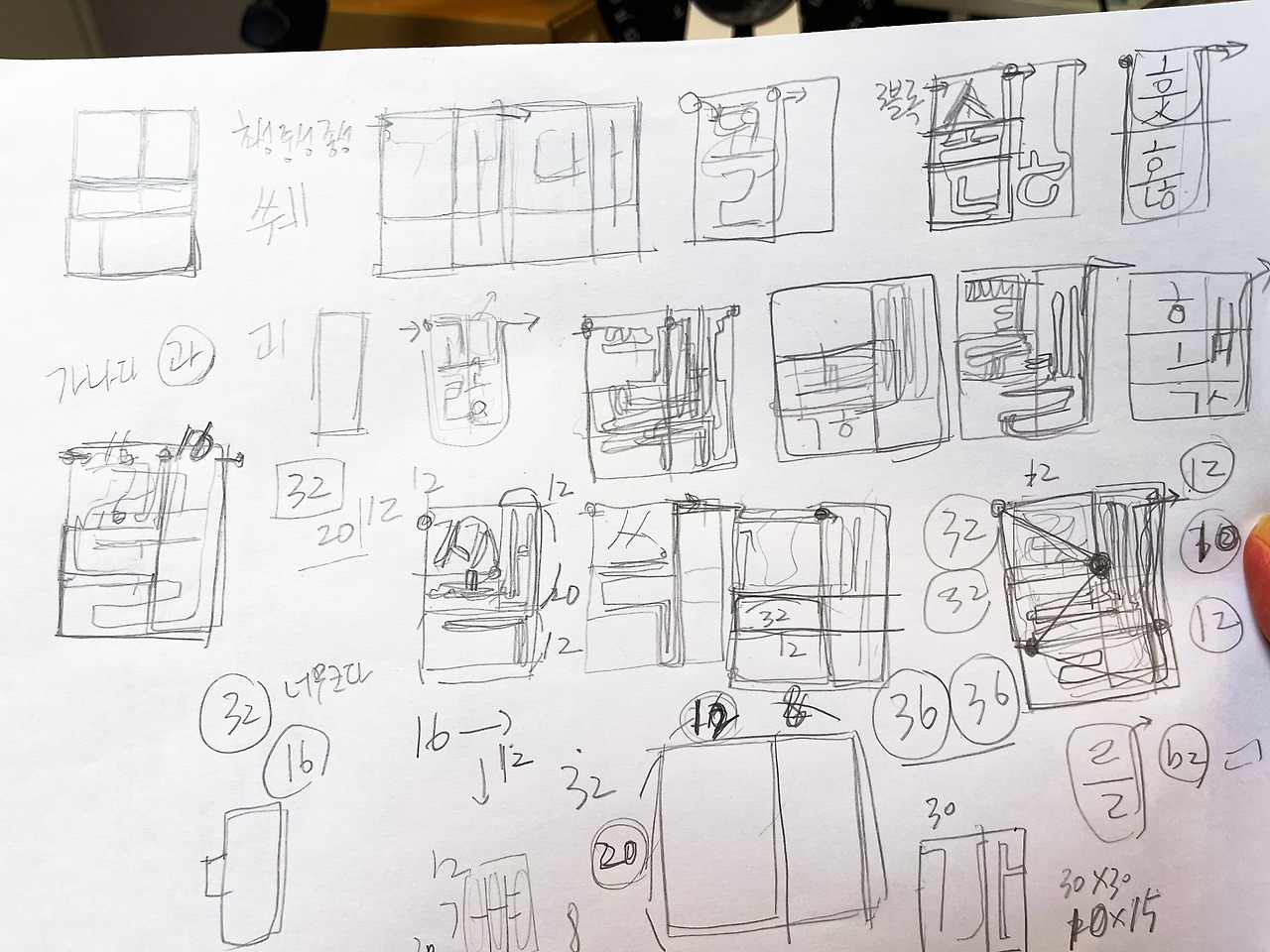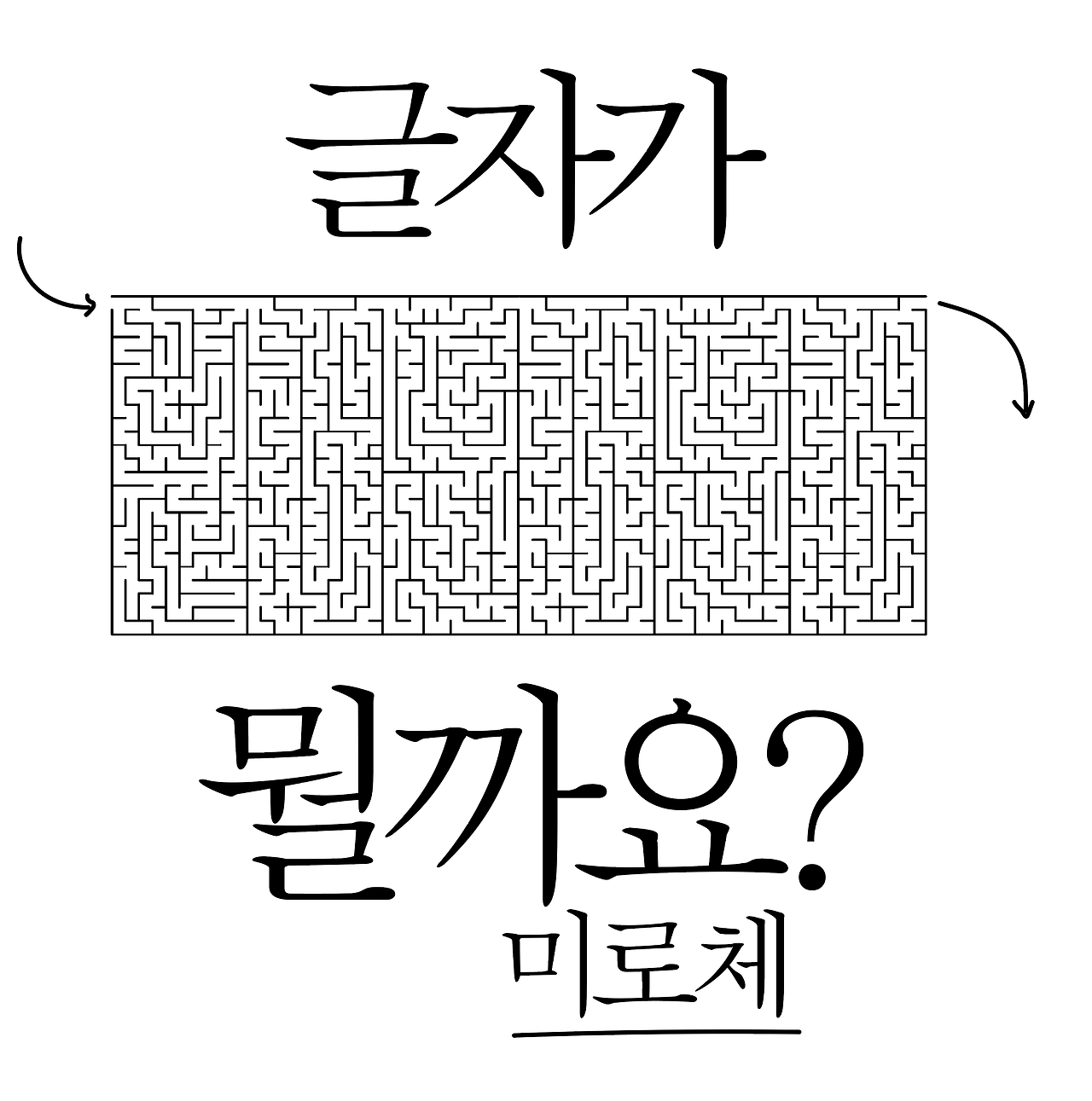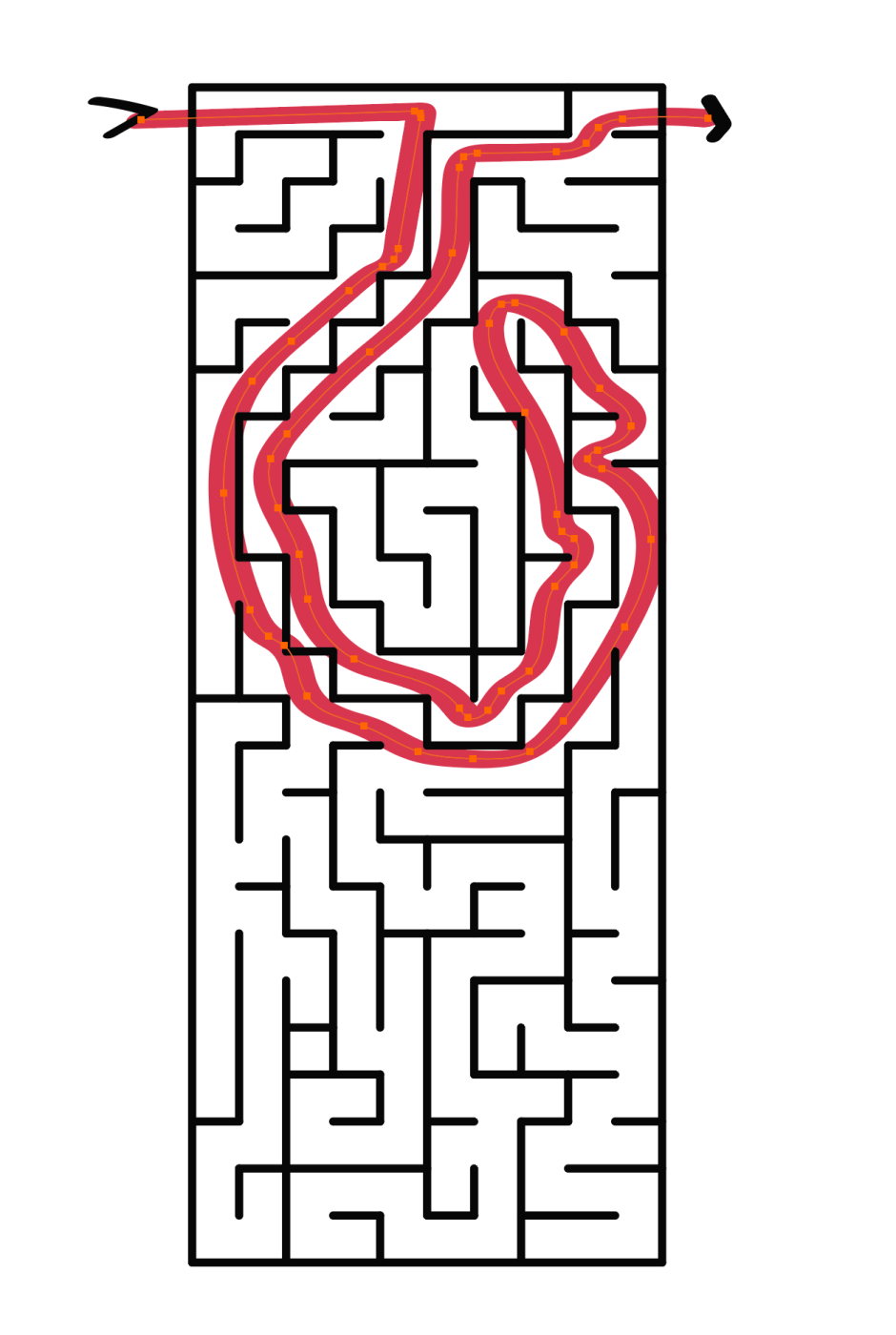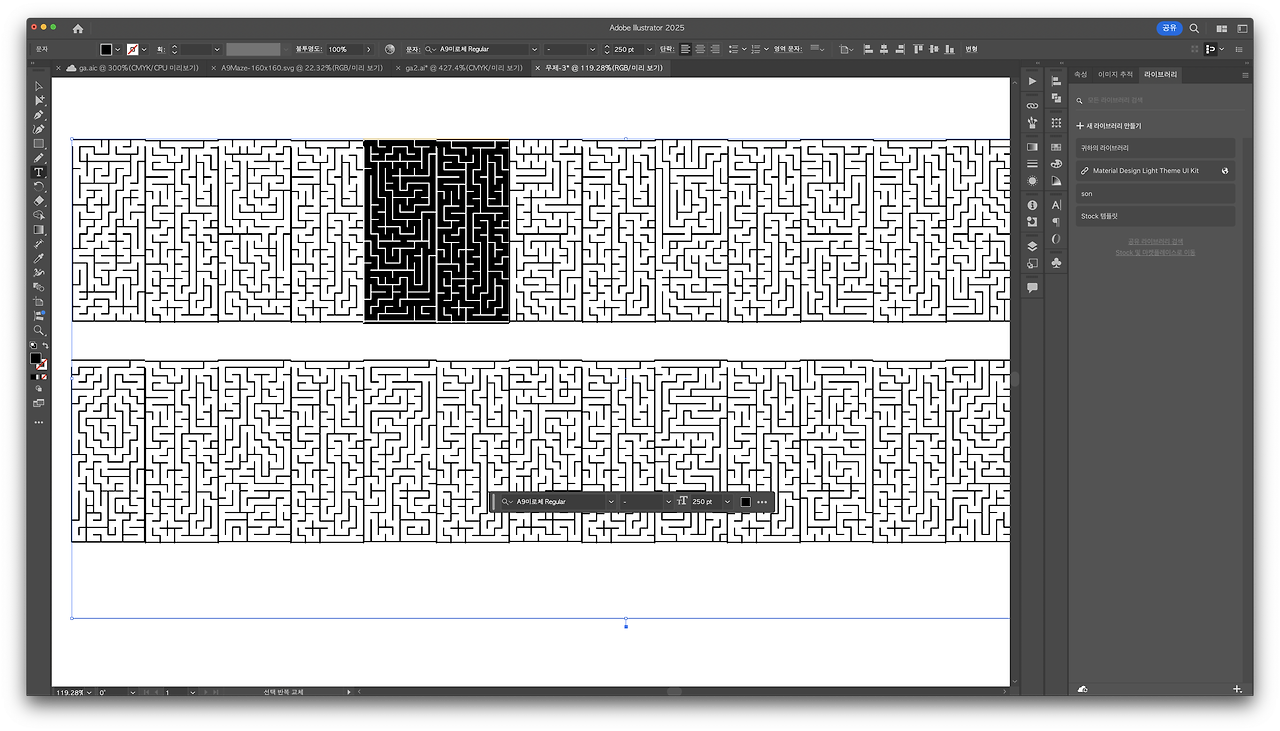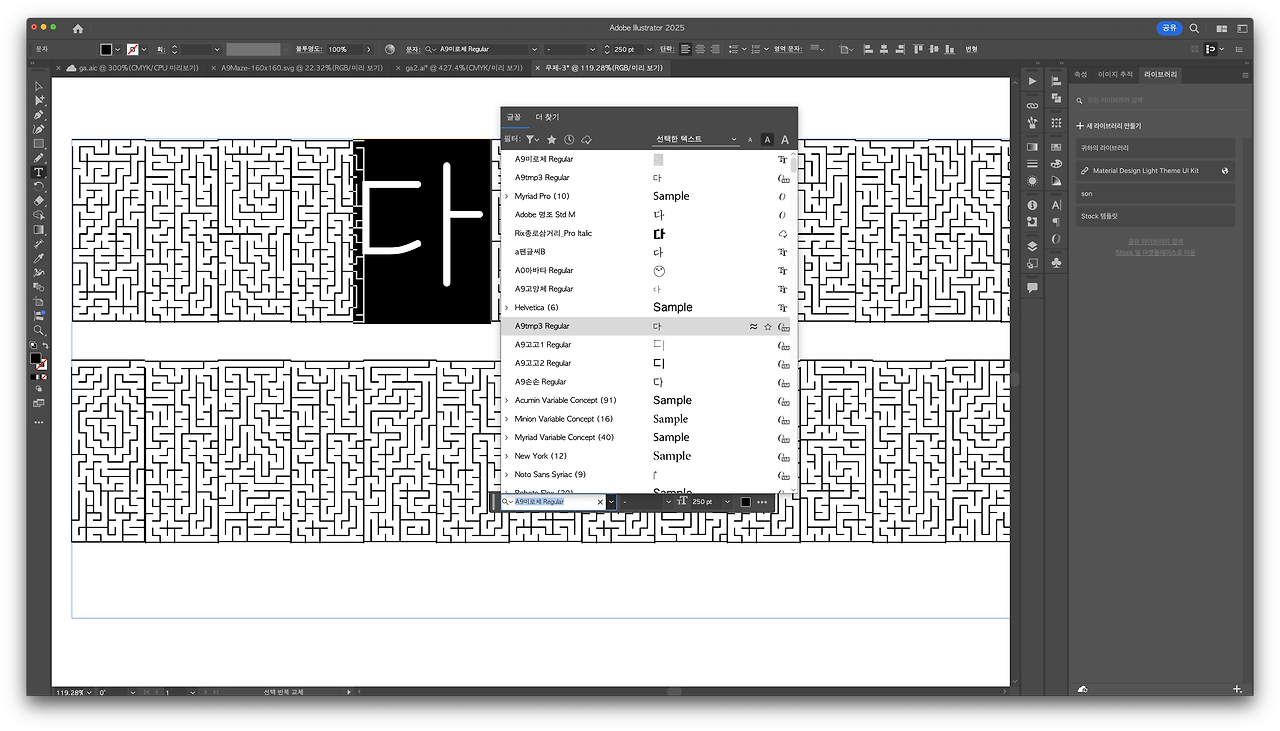
한글 미로 찾기 폰트 만들기 2
한글미로 찾기 폰트 만들기에 꽂혀서 주말반납했습니다.
일단 조합되는 글자에 특정한 위치를 연결해서 다음 초, 중, 종성이 특정한 위치로 연결되는 글자구성을 만들었고 너비, 높이를 맞춰서 최소한의 자모를 사용해서 폰트를 만들어볼 생각이었는데... 안예쁠거 같다 라는 생각으로 다시 사각형으로 맞췄습니다.
a9미로체 폰트패밀리에 실제 폰트로 구성한 미로스타일도 준비하고 있습니다.
그냥 일반 한글 폰트로 바꾸면 다 자가 나옵니다.
가나다라~ 하 이고 진짜 주말 날림
아주 정확하게 좌표를 잡으면 병풍느낌이나 반전했을 때 도장느낌의 글자가 될거 같습니다.
미로를 지나가서 통과하면 지나간 부분에 글자가 나타납니다. 길은 한개 앱으로 만들어서 키워볼만은 할거 같지만 지금은 먼저 다른 일부터
생각하고 프로토타입까지는 금방하지만 결과물을 위한 완성도는 아예 다른 작업이라 어린이 한글 책 내용에 넣어볼 생각입니다. ^^;;;